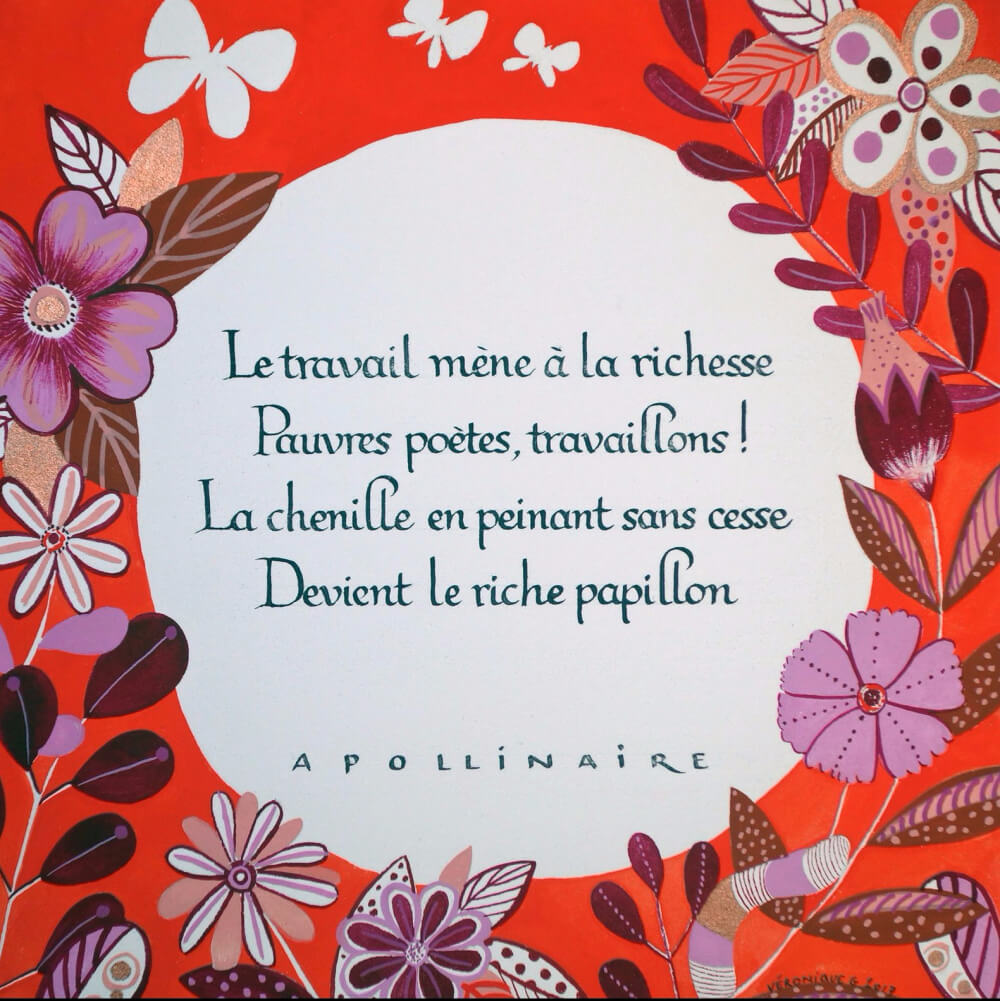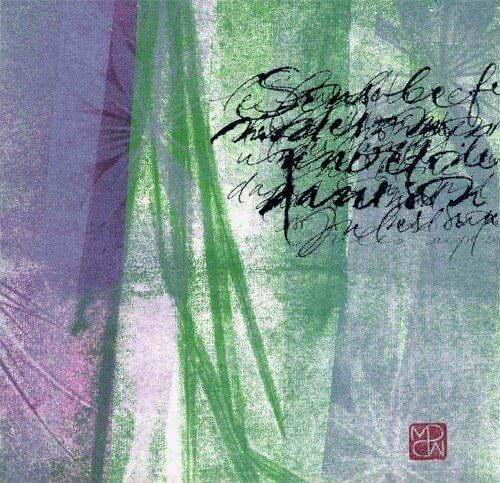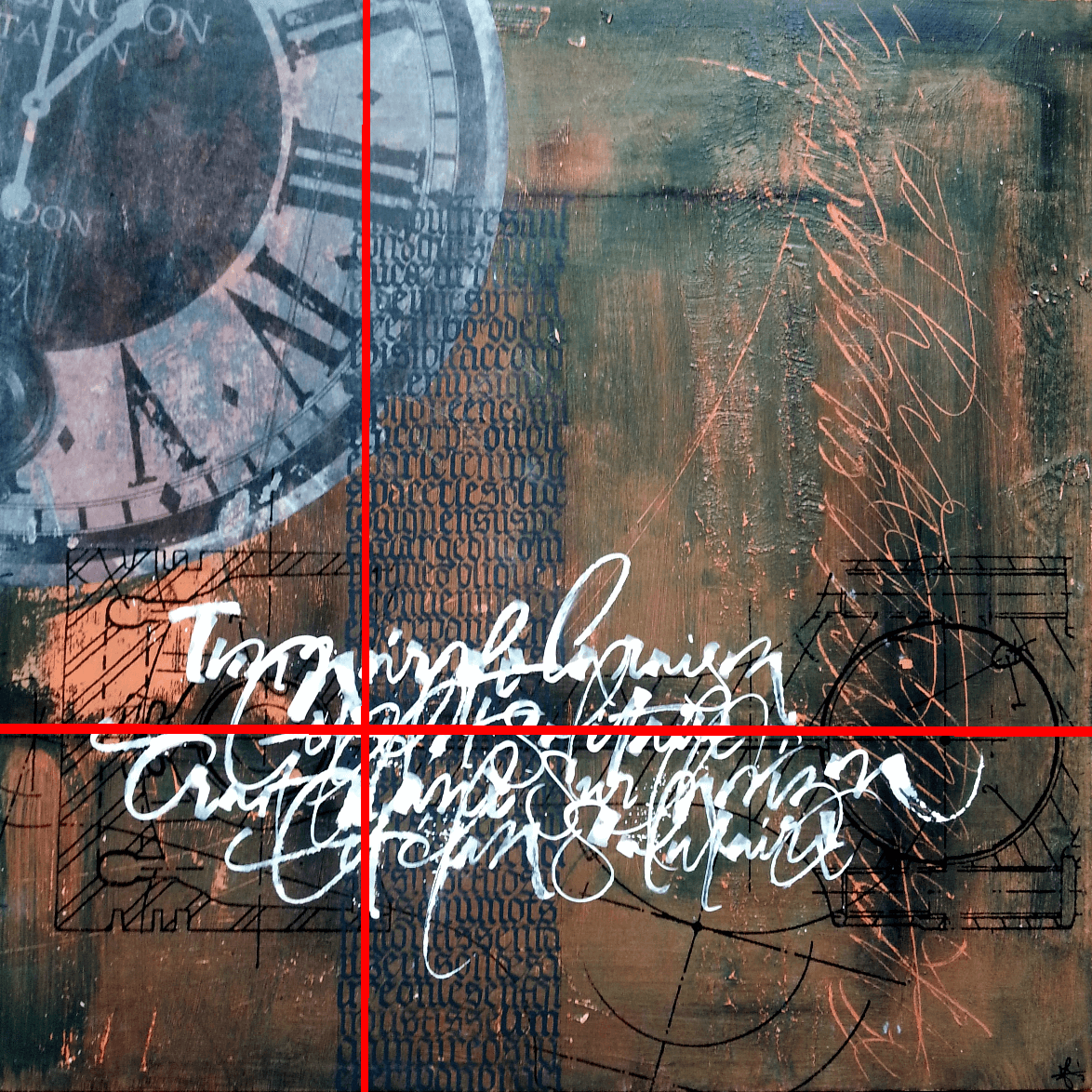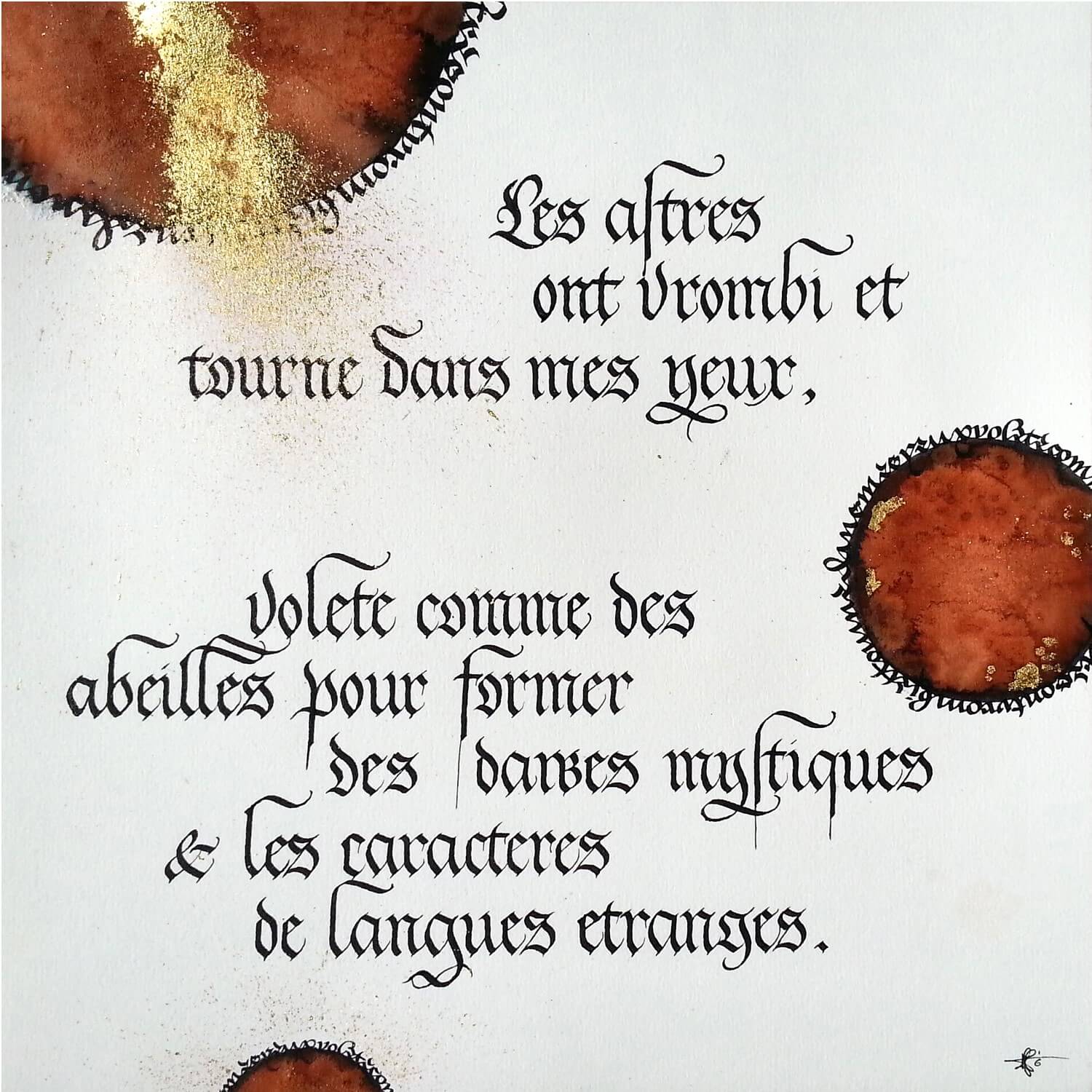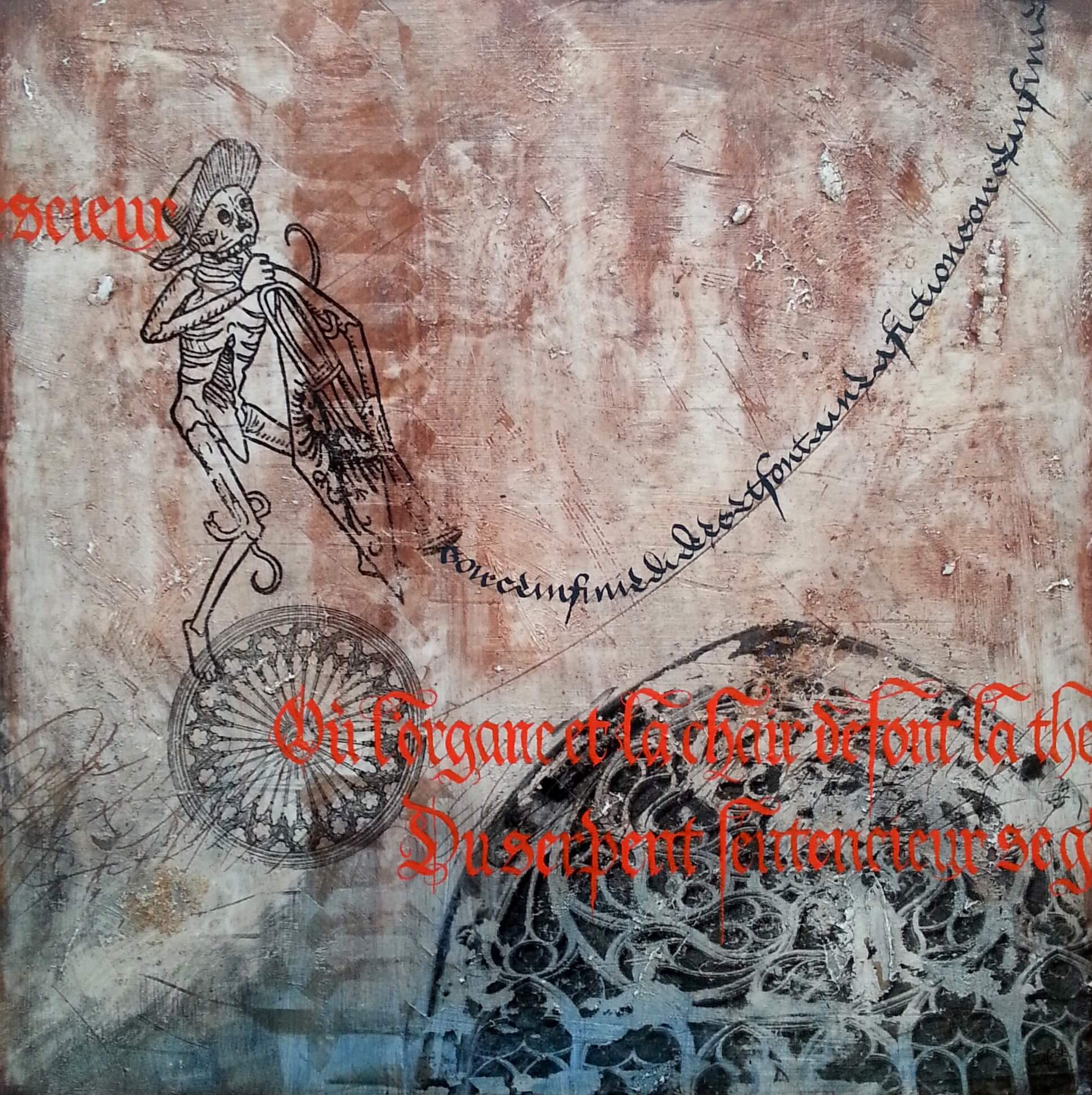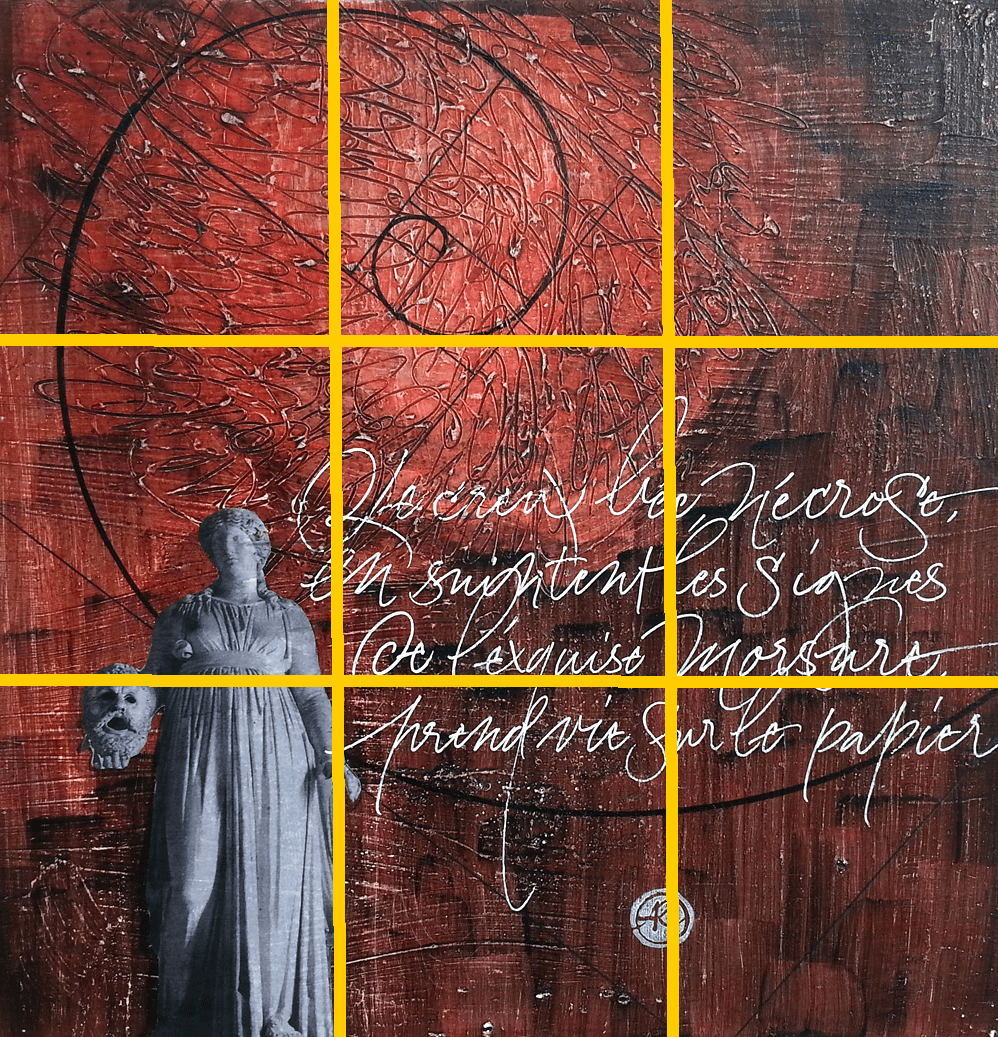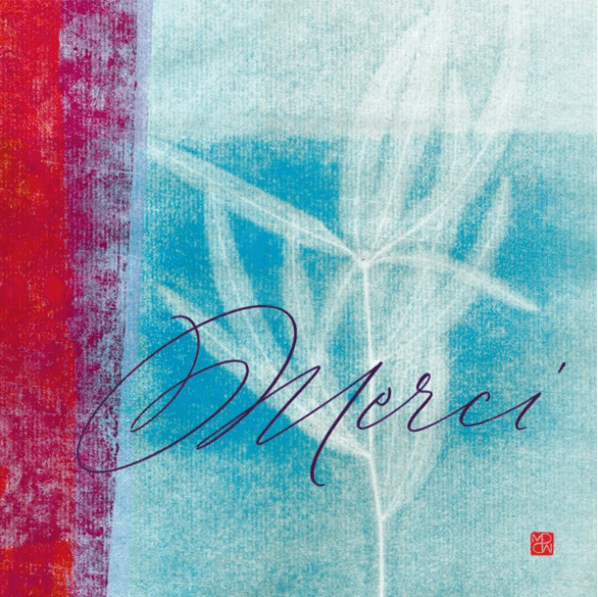
Nous sommes souvent un peu démunis lorsqu’il s’agit de mettre en page une belle calligraphie. Moi-même je fonctionne plutôt à l’instinct : ça passe ou ça casse ! A l’idée de travailler une composition plus élaborée, j’ai plutôt tendance à me crisper et à sur-réfléchir, en agitant règle, équerre, compas et calculette… Ceci pour peu de résultat voire au détriment de l’écriture elle-même !
C’est un questionnement fréquent pour nous autres calligraphes en herbe, et c’est en échangeant avec une autre calligraphe, Agathe Richard, que ma lanterne s’est subitement éclairée. Nous avons donc décidé de vous fournir un morceau écrit à 4 mains sur le sujet « calligraphie et composition », et de vous livrer 4 règles très simples pour calibrer votre mise en page.
Règle N°1 : la règle des tiers
La règle des tiers consiste à placer les personnages, objets importants ou tout autre élément clef sur des lignes imaginaires qui divisent l’image en parties égales. Ces lignes doivent être placées aux tiers horizontaux et verticaux. On les appelle les lignes de force et leurs intersections des points forts.
C’est une règle très connue pour le cadrage, que vous connaissez peut-être si vous pratiquez la photographie.
Quand on calligraphie, ça donne quoi?
Sur la première calligraphie, le bloc de textura grise vient s’appuyer sur la ligne du premier tiers vertical, tandis que l’axe de symétrie de la bielle transférée sur le fond correspond à la ligne du deuxième tiers horizontal. Sur la deuxième calligraphie, le centre de la spirale ainsi que l’esperluette (&) qui forme l’œil de l’entité à droite correspondent chacun à un point fort.
Cette règle n’est pas universelle, mais garder en mémoire qu’il faut privilégier les compositions en trois tiers plutôt qu’en deux moitiés constitue un bon point de départ.
Règle N°2 : le hors-champ
Le hors-champ est la partie de la scène qui n’apparaît pas dans un plan d’un film parce qu’elle n’est pas interceptée par le champ de l’optique de la caméra (Wikipédia). En d’autres termes, c’est ce qui est autour de l’image mais que l’on ne voit pas, que l’on ne peut qu’imaginer.
« Dans la construction narrative de l’image, le hors-champ crée un mystère, un effet d’ellipse, un vide à combler par l’imagination, casse la chaîne causale. Dans la construction de la composition de l’image, le hors-champ crée un vide, une aspiration vers la périphérie, un déséquilibre dynamique. » Source http://photonumerique.codedrops.net/
Fort bien, mais qu’est-ce que cela signifie pour nos calligraphies ? Et bien cela signifie qu’il ne faut surtout pas enfermer notre calligraphie dans le cadre, mais lui laisser des portes d’entrée et de sortie.
Sur cette calligraphie très centrée, le centre du cercle où apparait le texte est positionné dans le tiers central (Règle des tiers). Les fleurs et feuillages viennent dans le cadre, mais ne sont pas dessinés intégralement, laissant penser que le foisonnement se poursuit au-delà de la calligraphie.
Les explications d’Agathe :
« Sur la première calligraphie, j’ai volontairement placé mes trois astres en partie hors-champ, pour suggérer un univers plus vaste, que je ne voulais pas réduit à ma simple feuille. Sur la deuxième calligraphie, on voit bien le texte rentrer, être digéré par le squelette, puis ressortir du cadre en deux endroits différents. Dans les deux cas, le fait d’avoir pris en compte le hors-champ dans ma composition donne l’illusion que ma calligraphie est un instantané d’un univers qui la dépasse. Dès lors, les compositions ont beaucoup plus de profondeur. Sur la deuxième calligraphie, notez par ailleurs l’importance des lignes et des points de force dans la composition du tableau (règle des tiers) ».
Règle N°3 : La lecture en Z
C’est une règle de composition beaucoup utilisée en publicité, mais aussi dans la conception des pages web. Le principe est plutôt simple: d’une manière générale, notre œil effectue une lecture en Z quand on prend un document en main pour la première fois. Il commence en haut à gauche, chemine vers la droite, traverse le document et recommence.
Source : http://agence-autrement.com/le-sens-de-lecture-dans-la-publicite/
Cette règle est tout à fait compatible avec les deux règles précédentes. Voici ce que cela peut donner en calligraphie :
Les explications d’Agathe :
« J’ai réalisé cette calligraphie en gardant à l’esprit :
– la règle des trois tiers: signature et statue qui s’appuient sur les lignes de force, qui elles-mêmes coupent la spirale en des endroits clés
– le hors champ: la spirale, sa structure, la statue ainsi que le texte sortent tous du cadre
– la lecture en Z: la composition générale fait voyager le regard selon un chemin qui lui est naturel. »
Règle N°4 : « Less is more »
Une fois qu’on a fait un beau fond, ou même sur une simple feuille blanche, il ne faut pas vouloir remplir l’espace à tout prix. L’idée est évidemment de calligraphier, mais il est important de laisser respirer la composition, de laisser à voir le joli fond qu’on s’est souvent donné du mal à faire.
On veut parfois trop remplir notre feuille alors que quelques mots savamment placés suffisent. Pour ce faire, il peut être judicieux de calligraphier les quelques mots en questions sur un calque pour pouvoir ensuite les faire glisser à l’envi sur notre fond et ainsi trouver leur juste place.